Нулевая перечеркнутая цифра: где включить slashed zero
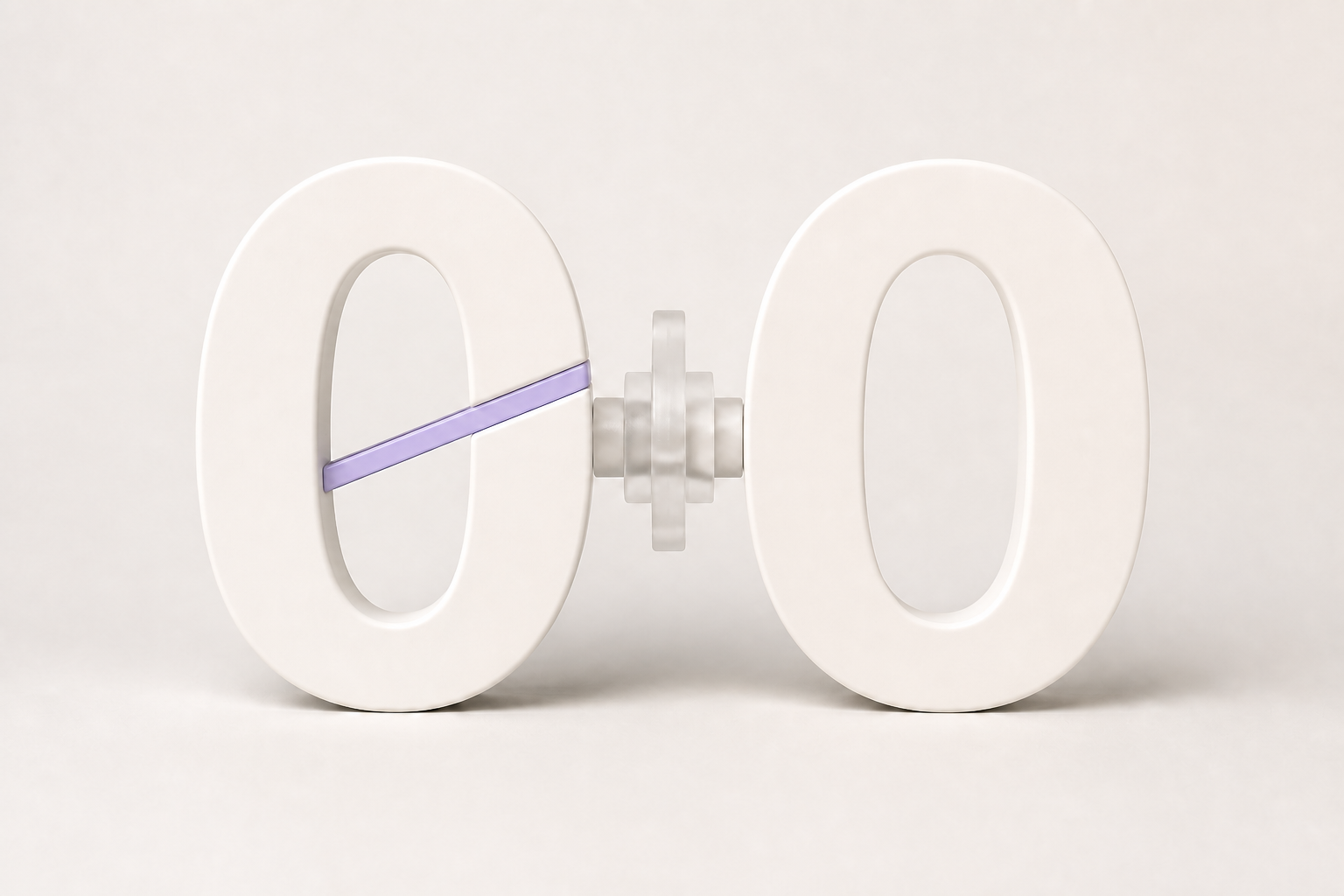
Нулевая перечеркнутая цифра включается не отдельной клавишей, а через функцию шрифта slashed zero, если гарнитура её поддерживает. В редакторах и терминалах настройка находится в параметрах шрифта или OpenType, а в вебе задаётся через CSS. Ниже разберём, где искать функцию, как проверить результат и почему она иногда не срабатывает.
Что означает перечеркнутый ноль в шрифте
Перечеркнутый ноль — это альтернативное начертание цифры 0, в котором внутри знака проходит диагональная черта. В типографике такой вариант обычно называется slashed zero или zero slash. Он нужен не для украшения текста, а для быстрого различения нуля, буквы O, кириллической О и иногда похожих символов в коде, серийных номерах и технических обозначениях.
Обычный ноль и перечеркнутый ноль имеют один и тот же Unicode-символ U+0030. Это важно: slashed zero не является отдельным знаком, который можно вставить универсальным кодом. Программа показывает ту же цифру в другой глифовой форме, если активирована соответствующая OpenType-функция шрифта.
Не следует путать перечеркнутый ноль с символом пустого множества или с буквой O, перечеркнутой вручную. Пустое множество относится к математической записи, а slashed zero является типографической альтернативой цифры. В коде значение символа не меняется: меняется только его визуальное отображение.
Как работает функция slashed zero
Функция slashed zero обычно обозначается OpenType-тегом zero. OpenType позволяет хранить в шрифте альтернативные глифы и правила их включения. Когда приложение поддерживает эту функцию, оно заменяет стандартный глиф цифры 0 на вариант с диагональной чертой, не изменяя сам текстовый символ и его копирование.
Поддержка зависит сразу от трёх условий: в шрифте должен быть предусмотрен альтернативный ноль, программа должна уметь применять OpenType-функции, а выбранный текстовый стиль должен использовать нужную гарнитуру. Если хотя бы одно условие не выполняется, настройка может отсутствовать или не давать видимого результата.
Где включить перечеркнутый ноль в разных программах
Редакторы макетов и графические программы
В Adobe InDesign, Illustrator, Photoshop и других программах с расширенной типографикой функция обычно находится в панели OpenType, панели «Глифы» или дополнительных параметрах символов. Выделите текст, выберите шрифт, откройте доступные функции OpenType и найдите пункт, связанный с перечеркнутым нулём. В некоторых интерфейсах он отображается как Slashed Zero, Zero Slash или «Перечеркнутый ноль».
Если отдельного переключателя нет, откройте панель «Глифы» и найдите альтернативную форму цифры 0 среди вариантов выбранного шрифта. Такой способ может вставить альтернативный глиф вручную, но поведение будет зависеть от программы и формата текста. Для повторяющихся текстовых стилей удобнее применять OpenType-функцию ко всему стилю.
Текстовые редакторы, IDE и редакторы кода
В IDE и обычных текстовых редакторах настройка встречается реже. Многие программы позволяют выбрать гарнитуру и начертание, но не дают доступа к стилистическим функциям OpenType. Если в настройках нет пункта slashed zero, используйте шрифт, в котором перечеркнутый ноль включён как стандартный вариант, либо найдите расширение и тему, поддерживающие эту возможность.
Для программиста важнее всего стабильная различимость символов в строках, логах и документации. Например, в записи O0l1 легко перепутать заглавную O, ноль, строчную l и единицу. Перечеркнутый ноль помогает визуально отделить 0 от O, но не решает проблему различия всех похожих знаков, поэтому стоит выбирать гарнитуру с хорошо разведёнными формами символов.
Терминалы и консоли
В терминалах чаще всего используется моноширинный шрифт, а возможность slashed zero зависит от самого терминального приложения. Откройте настройки профиля или окна терминала, перейдите к параметрам текста и выберите гарнитуру с перечеркнутым нулём. Если отдельного переключателя нет, проверьте, поддерживает ли терминал OpenType-функцию zero; многие простые консоли применяют только базовый набор глифов.
Веб-сайты и CSS
В веб-дизайне OpenType-функцию можно включить свойством CSS font-variant-numeric: slashed-zero. Для более точного управления используют font-feature-settings: "zero" 1. Второй вариант зависит от браузера и шрифта сильнее, поэтому перед публикацией проверьте отображение в целевых браузерах, на мобильных устройствах и при загрузке веб-шрифта.
Для интерфейсов с номерами заказов, кодами подтверждения и техническими идентификаторами перечеркнутый ноль может улучшить чтение. Однако не применяйте его автоматически ко всему сайту: в рекламных заголовках, длинном тексте и некоторых брендовых надписях диагональная черта создаёт лишний визуальный шум.
Нулевая перечеркнутая цифра — это OpenType-альтернатива обычного нуля, а не отдельный символ. Ищите функцию slashed zero в настройках шрифта, панели OpenType или CSS, а затем проверяйте результат на реальных строках, размерах и начертаниях. Для технических интерфейсов и кода такая форма особенно полезна, когда требуется быстро отличать 0 от O.